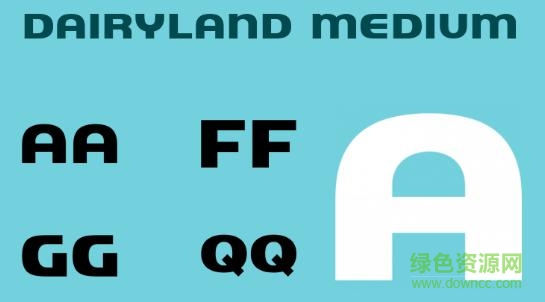
dairyland-中字體是一款非常有分量感的英文字體,線條粗且均勻,弧線圓潤(rùn),字型飽滿,給人的印象比較醒目,十分適合用作宣傳設(shè)計(jì)用字,需要的朋友快來(lái)下載吧!
1.跳躍明快
2.端莊秀麗
3.格調(diào)高雅
4.個(gè)性非常突出
5.具有重量感
6.字體的造型奇妙